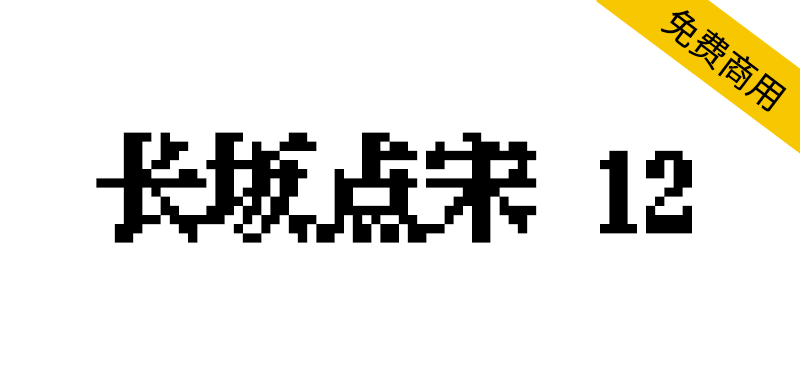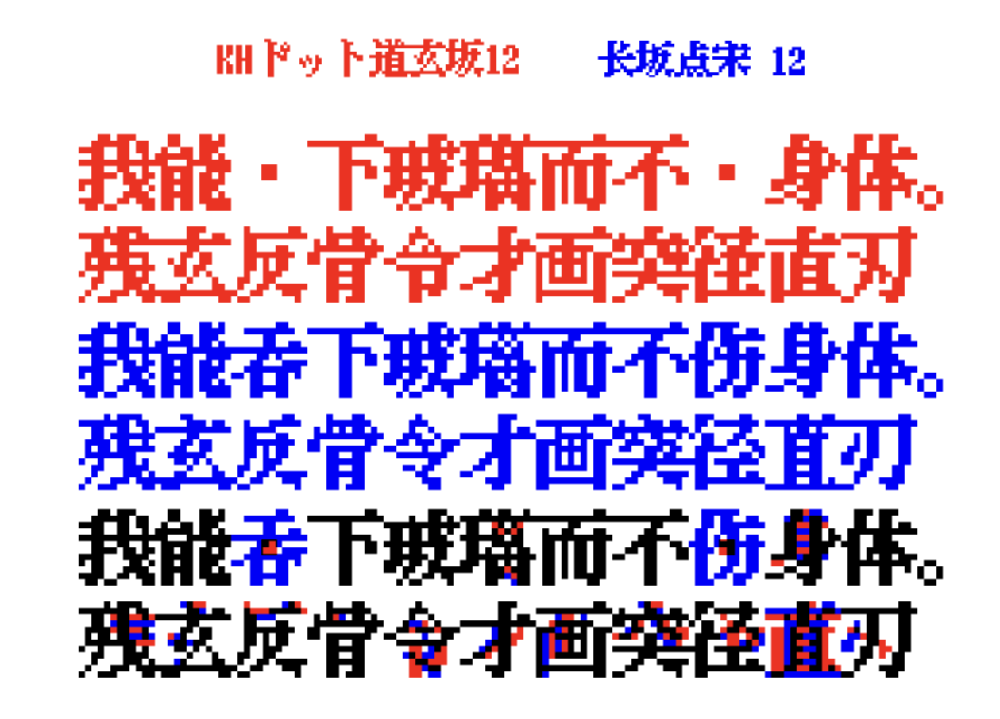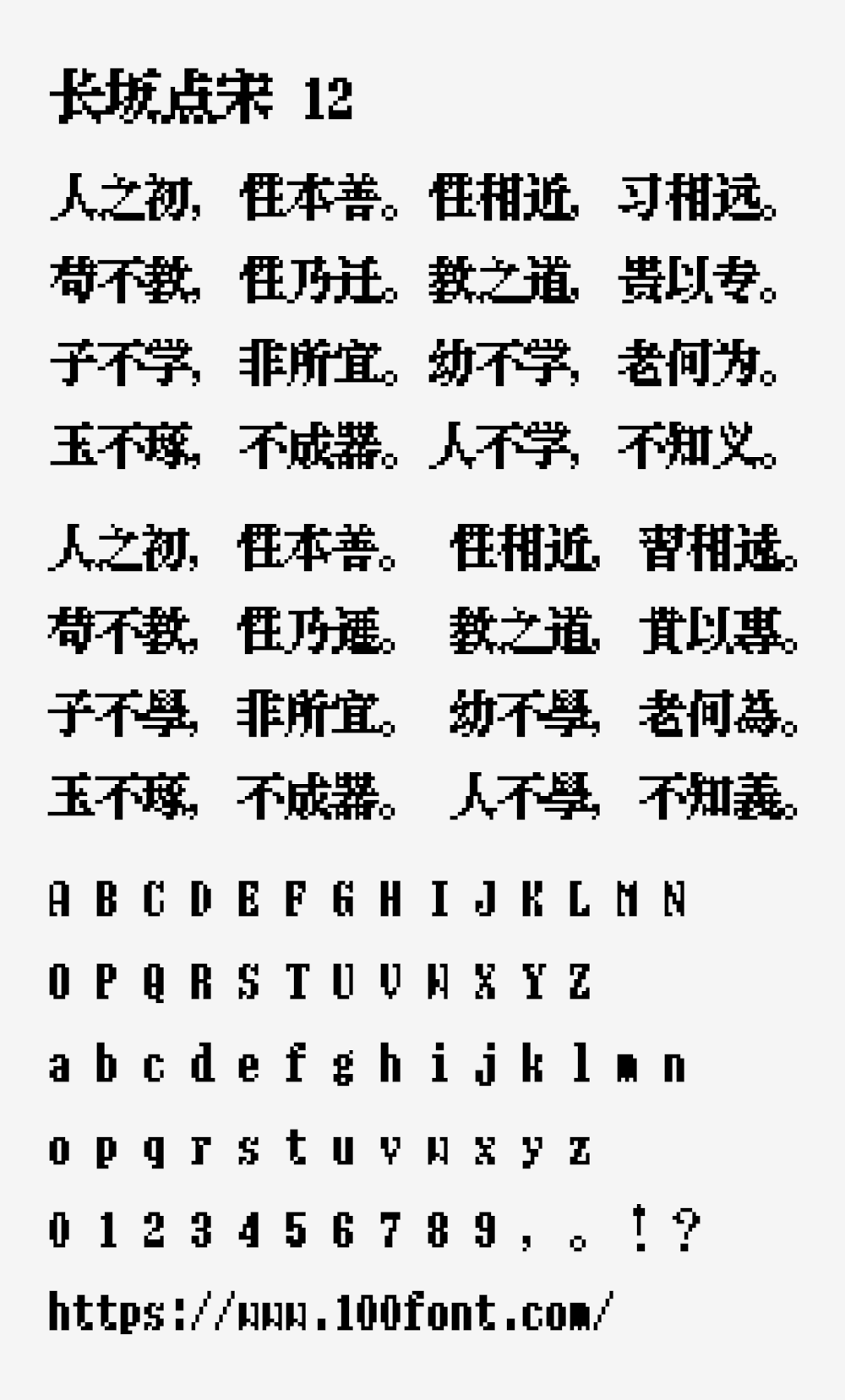
长坂点宋 12是基于 「KH点阵字体」中的「KHドット道玄坂12」补足简体字和部分繁体字的 12px 点阵粗宋体,适合在复古风格的游戏和招牌中使用。
修改内容:补全GB2312字符集中的所有汉字与部分常用繁体字,并调整部分汉字字形;补全汉语拼音与注音符号。此外,部分竖画较多的汉字(如衄、嗣、騙)的处理方式和原字体也有所不同。